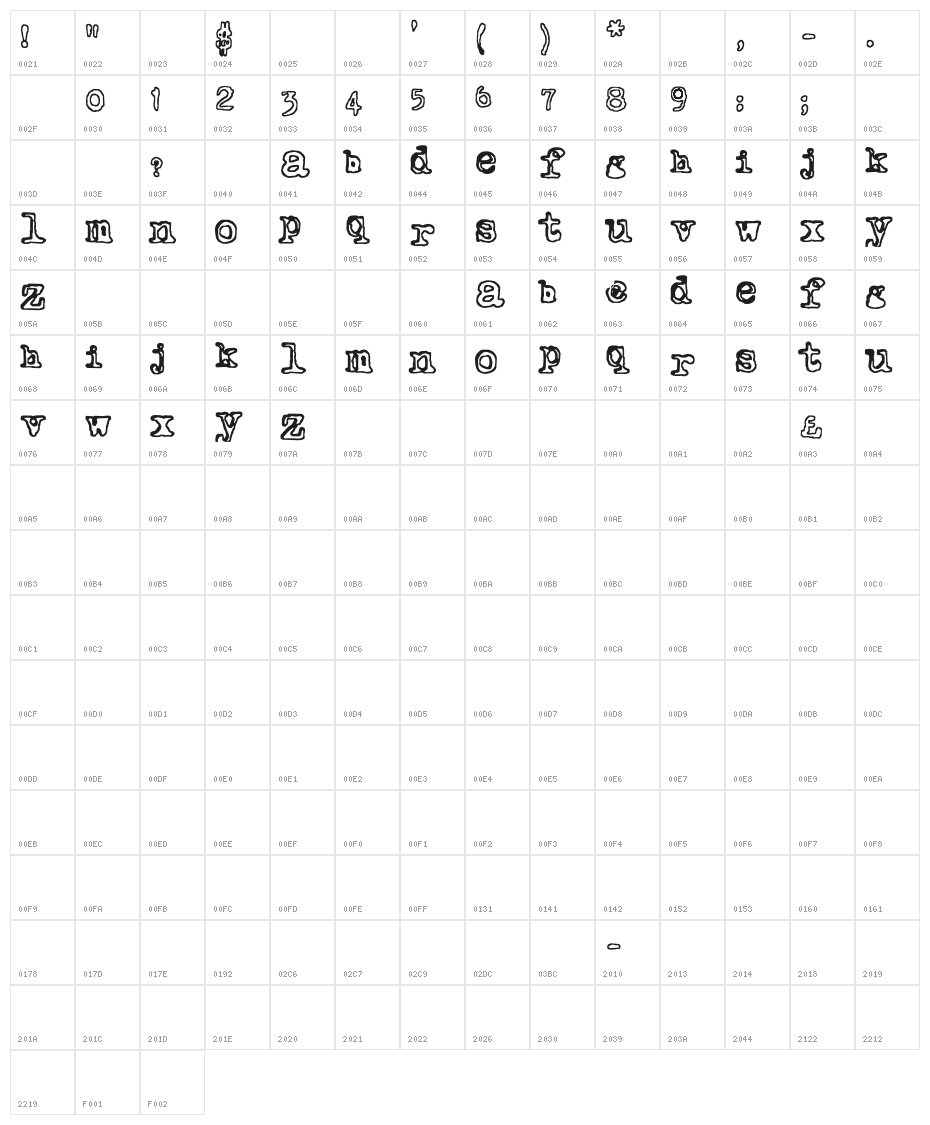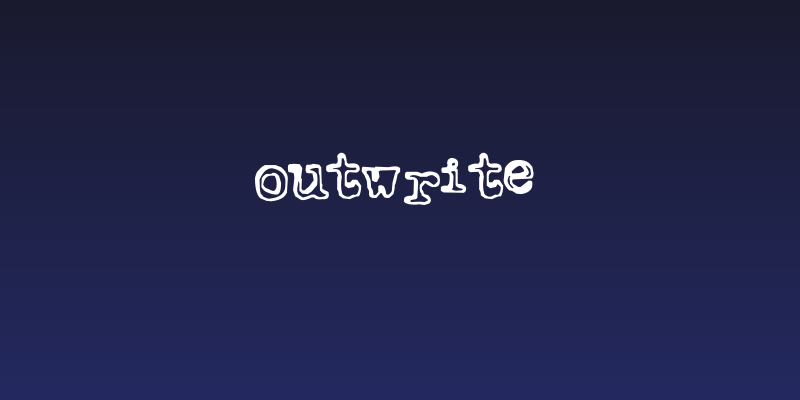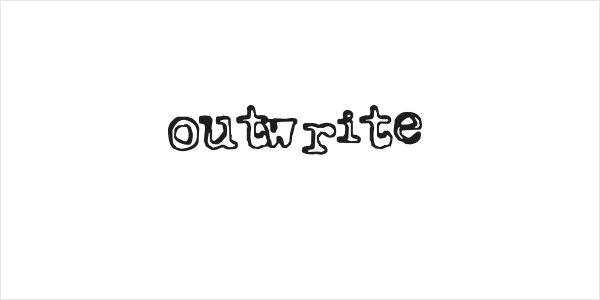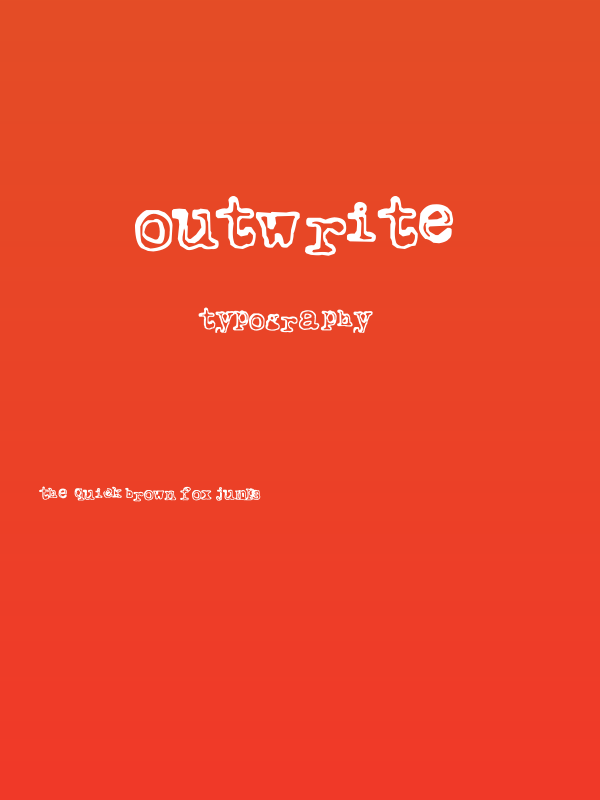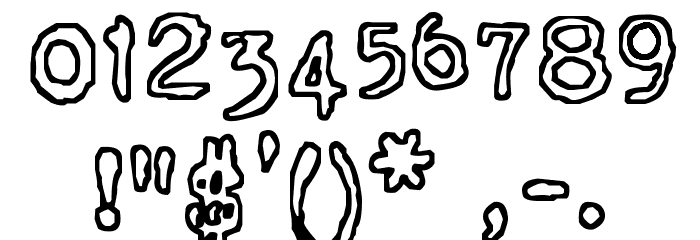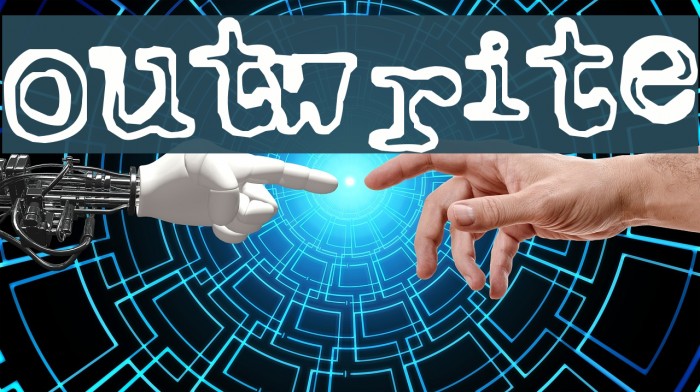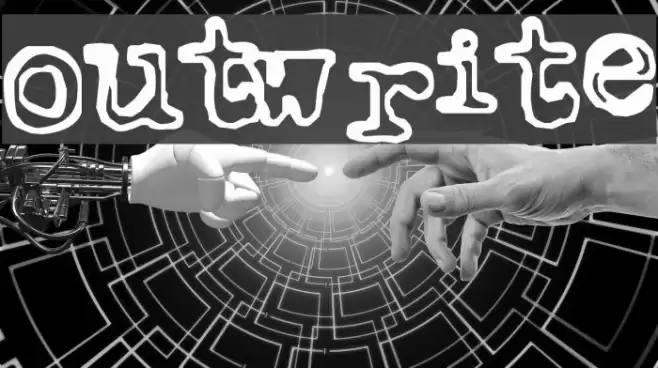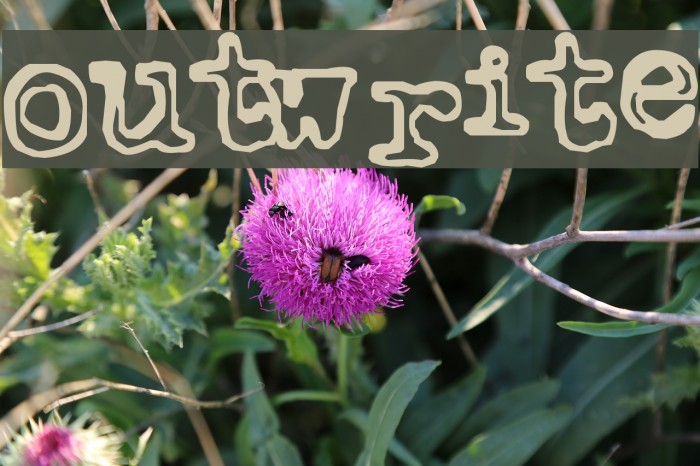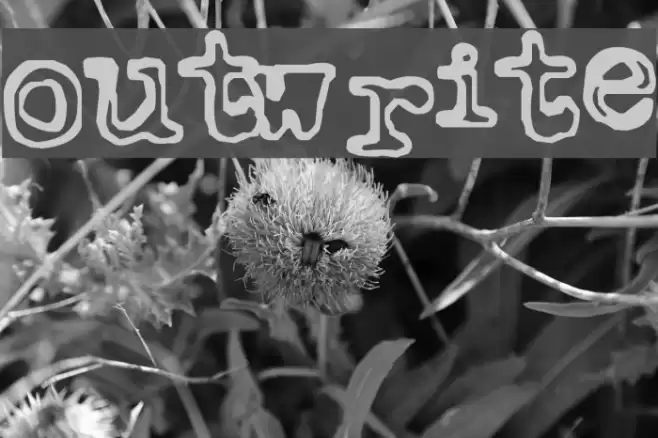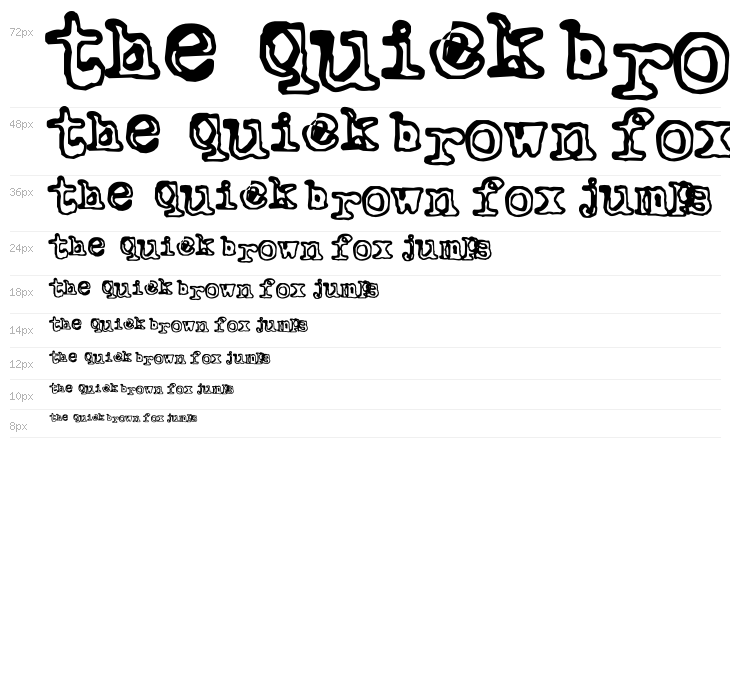
Outwrite Font
| Style général | Playful, Artistic, Whimsical |
| Cas d'utilisation | Headlines, Posters, Creative projects |
| Projets proposés | Ideal for children's books, comic strips, playful branding, and creative posters. |